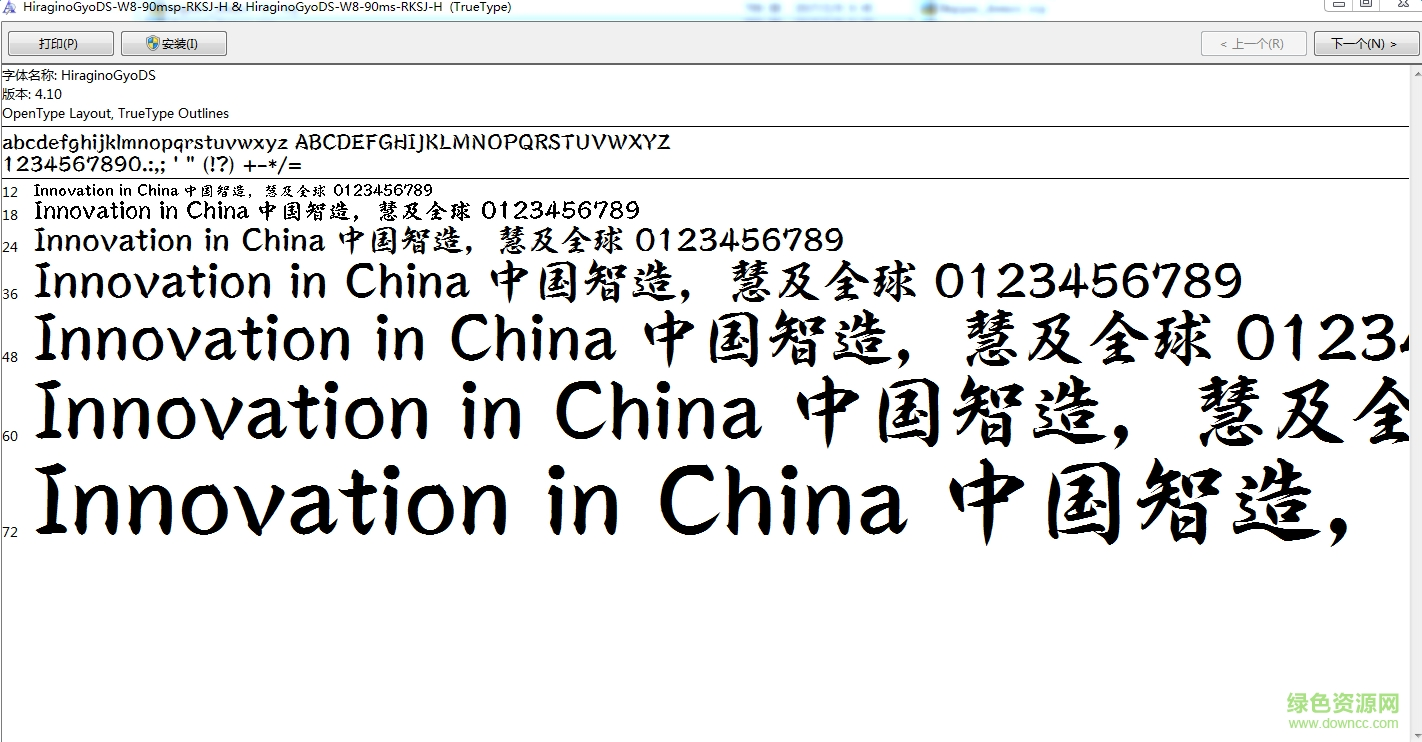
軟件介紹 軟件標簽: 特太行書字體 行書字體 特太行書字體是一款較粗的行書字體,筆墨濃重,沉穩(wěn)又不失大氣,可應用于文學設計、藝術創(chuàng)作、雜志報刊、印刷包裝等領域,需要該字體的小伙伴快來綠色資源網(wǎng)下載吧!字體安裝方法方法一:直接將字體復制到C:\WINDOWS\Fonts;方法二:控制面板/字體/文件/安裝新字體;方法三:針對win7系統(tǒng),用戶只需選中字體右鍵安裝即可。注意事項本站所有字體資源僅供個人學習與參考,如需商業(yè)使用請到相關官網(wǎng)授權。 軟件截圖 上一張下一張(1 / 1) 安裝詳細截圖 猜你喜歡 非主流字體 行書字體 非主流字體 非主流字體大全收錄了國際音標字體ipapanadd、五線譜字體akvo.ttf、等寬編碼字體、立體英文字體、eva明朝體、特殊黑體字體、英文花體字體等各式好看的非主流字體,中英文都有! 查看更多>> code free font 2.44M/中文/5.0/下載 ipapanadd.ttf 250KB/中文/1.0/下載 akvo.ttf字體 120KB/中文/2.2/下載 englishling字體 2.44M/中文/1.9/下載 vineta bt普通(西方) 95KB/中文/5.0/下載 eva明朝體 23.43M/中文/1.0/下載 行書字體 行書字體包括了鋼筆字行書字體大全、硬筆行書字體等,是一種介于楷書和草書之間的字體。為什么這樣說?因為行書字體既有草書的流暢感,又有楷書的端正感,可以說,行書結合了草書和楷書的特點,形成了獨特好看的行書字體。喜歡的朋友,趕快下載體驗吧! 查看更多>> 繁體行書字體 9.76M/中文/4.0/免費版下載 winman tun10011字體 17.57M/中文/6.6/下載 南構嘉飛行書字體 10.00M/中文/6.6/下載 c g流麗行書體繁/簡 4.39M/中文/5.0/下載 北方行書簡體 2.63M/中文/7.2/下載 qxyingbixing 1.26M/中文/8.0/下載 其他版本下載 標題 大小 更新日期 下載 下載地址 電腦版 特太行書 ttf版 點擊報錯 軟件無法下載或下載后無法使用,請點擊報錯,謝謝! 關閉報錯反饋 請描述您所遇到的錯誤,我們將盡快予以修正,謝謝! *必填項,請輸入內容 本類最新 dreamweaver字體庫 首爾南山體字體 v1.06 官方版 潮字社風云簡ttf 潮字社凌渡鯤鵬簡體字體 潮字社曾玉波手書簡字體 微博慧心字體 用戶評論 熱門評論 最新評論 發(fā)表評論 查看所有評論(0) 昵稱: 請不要評論無意義或臟話,我們所有評論會有人工審核. 字數(shù): 0/500 (您的評論需要經(jīng)過審核才能顯示)